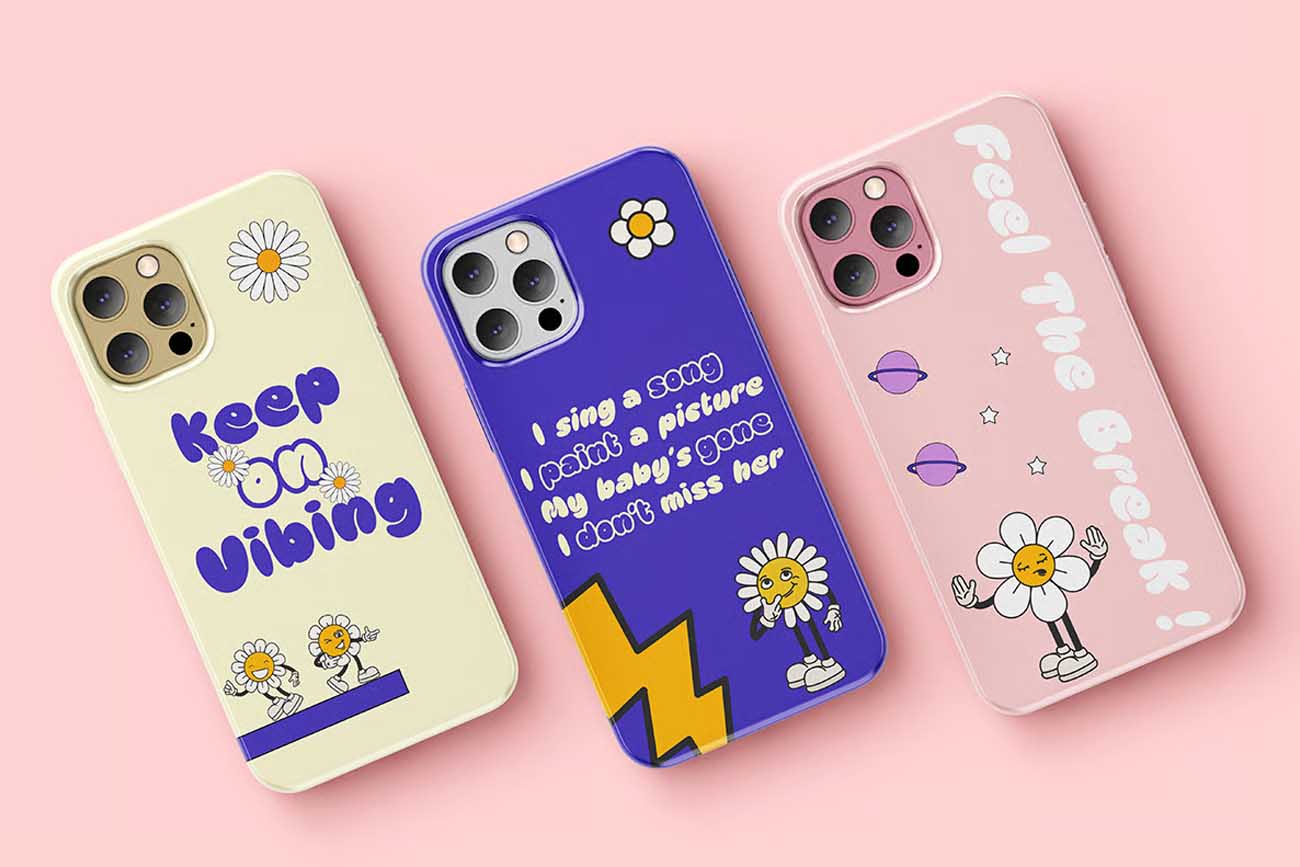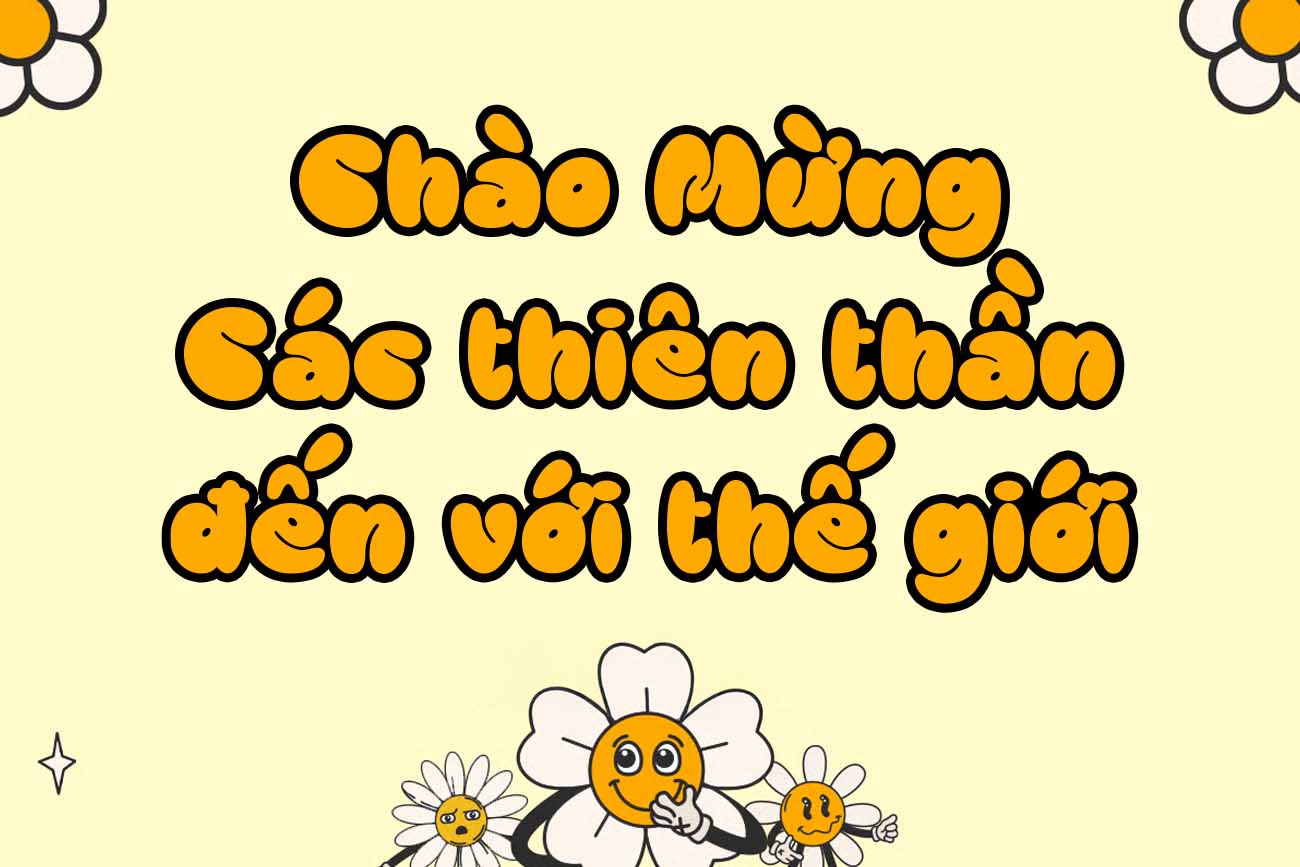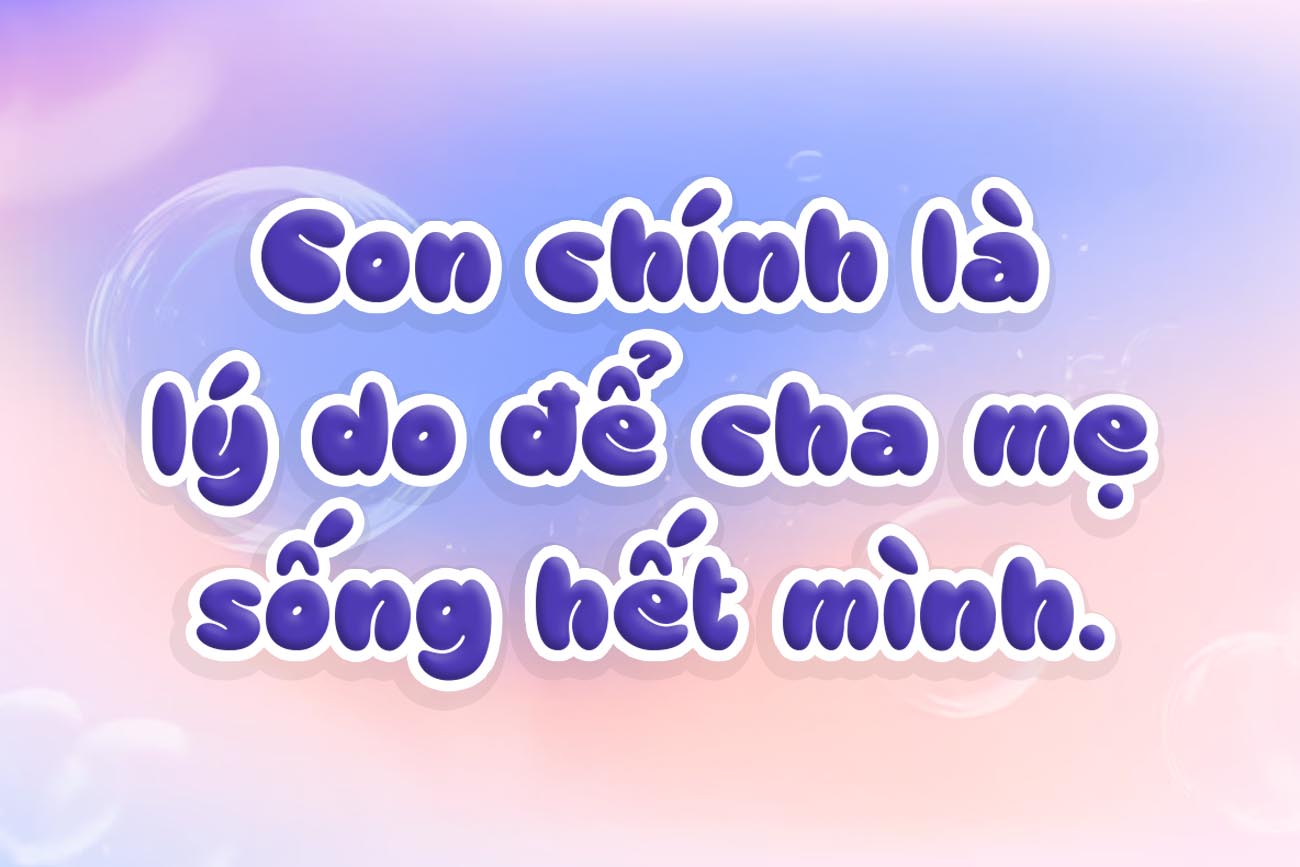
Font Chữ Hoạt Hình TH Playful Bubble Việt Hóa – Vui Nhộn & Đáng Yêu
Font Chữ Playful Bubble Việt Hóa – Vui Nhộn & Gần Gũi
Playful Bubble là một kiểu chữ sans-serif mang phong cách “bubble” đáng yêu, được thiết kế bởi Flat – một nhà thiết kế font nổi tiếng với các sản phẩm mang hơi hướng vui nhộn, trẻ trung. Các ký tự được bo tròn, căng đầy như bong bóng, mang lại cảm giác mềm mại và thân thiện ngay từ ánh nhìn đầu tiên.
Phiên bản Việt hóa do Phạm Sơn thực hiện đã tối ưu toàn bộ bảng ký tự tiếng Việt, bao gồm đầy đủ dấu thanh và ký tự đặc biệt, giúp font hiển thị hoàn hảo trong mọi dự án thiết kế.
Điểm nổi bật của Playful Bubble là đường nét tròn trịa, độ dày ký tự đồng đều, tạo sự cân đối và dễ đọc. Phong cách này đặc biệt phù hợp với logo thương hiệu trẻ em, bao bì bánh kẹo, poster sự kiện trường học hoặc các ấn phẩm mạng xã hội mang tính giải trí.
Khi sử dụng, font tạo ấn tượng thị giác mạnh ngay cả ở kích thước lớn, giúp tiêu đề và thông điệp nổi bật. Nhờ được Việt hóa chuẩn, Playful Bubble khắc phục hoàn toàn lỗi hiển thị dấu – vốn là nhược điểm của nhiều font quốc tế khi dùng với tiếng Việt.
Trải nghiệm thực tế cho thấy, font trở nên sinh động khi phối cùng gam màu pastel hoặc nền sáng, dễ dàng mang đến bầu không khí tích cực cho thiết kế. Dù bạn là designer chuyên nghiệp hay người mới, Playful Bubble sẽ giúp ý tưởng của bạn thêm phần gần gũi, đáng yêu và thu hút.